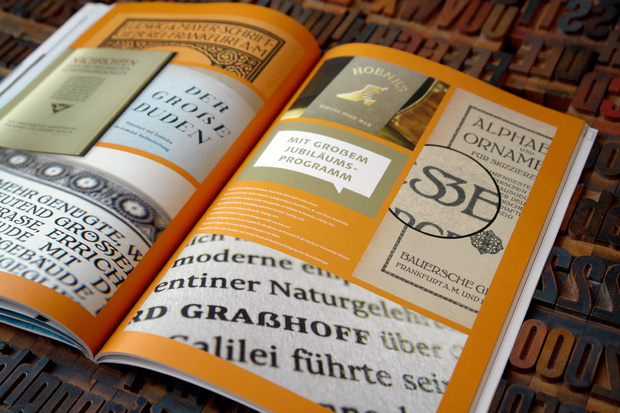
Das Eszett kommt endlich groß heraus
30 Kleinbuchstaben, doch nur 29 Großbuchstaben — das Alphabet in Deutschland und Österreich ist nicht komplett. Eine verschmerzbare, geschichtlich bedingte Eigenheit oder ein Grund zu handeln?